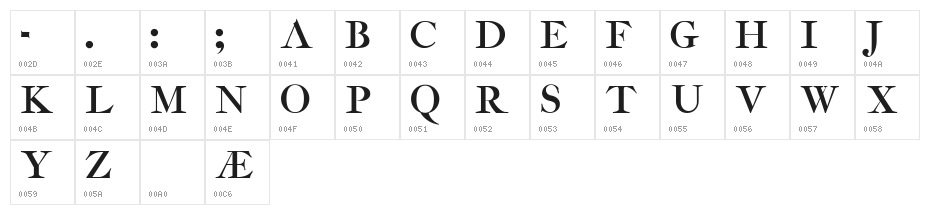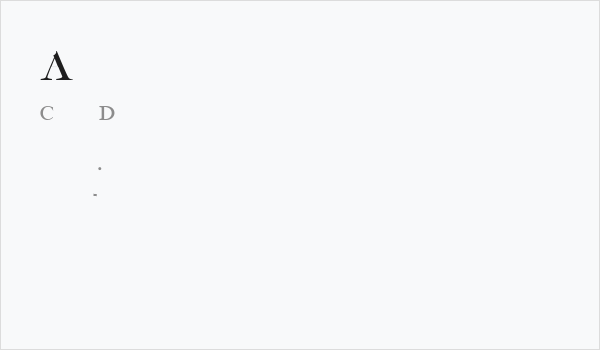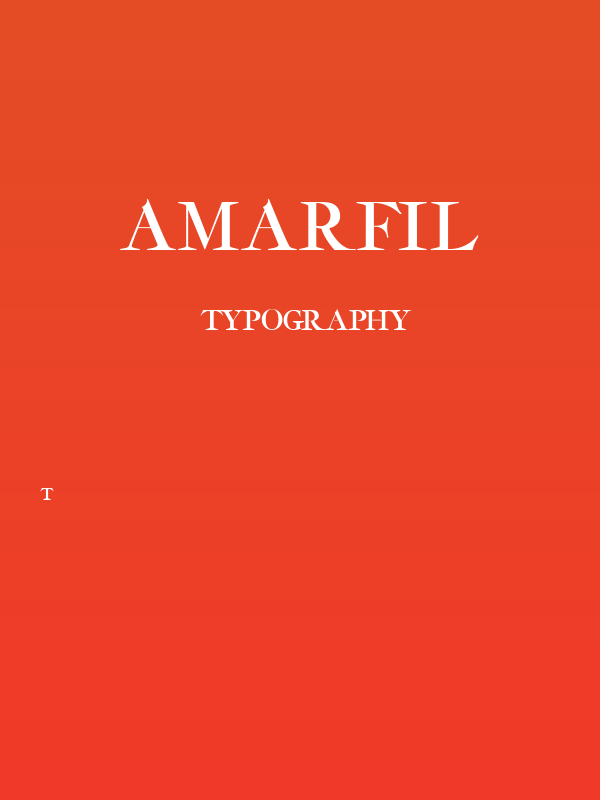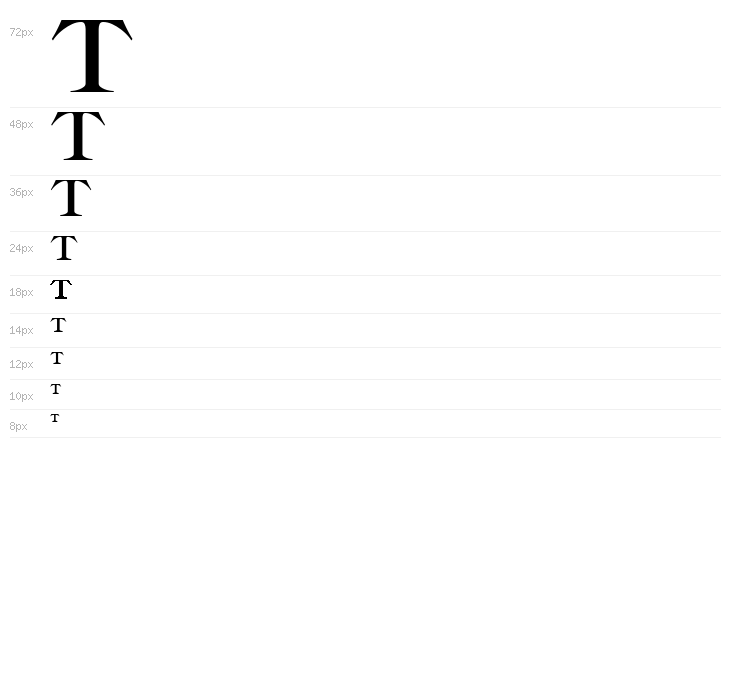
Amarfil Font
✎ Serif
| Progetti proposti | Ideal for use in editorial design, book covers, formal invitations, branding for luxury products, and corporate identity materials. |